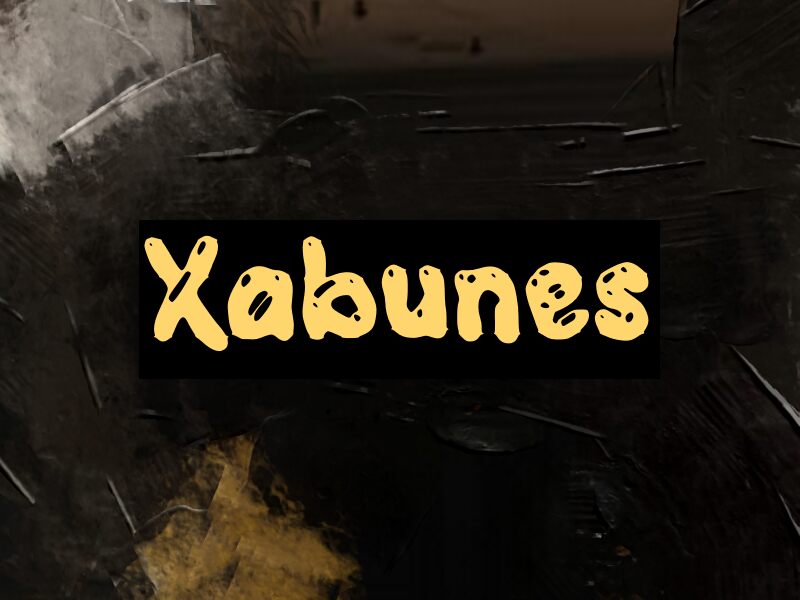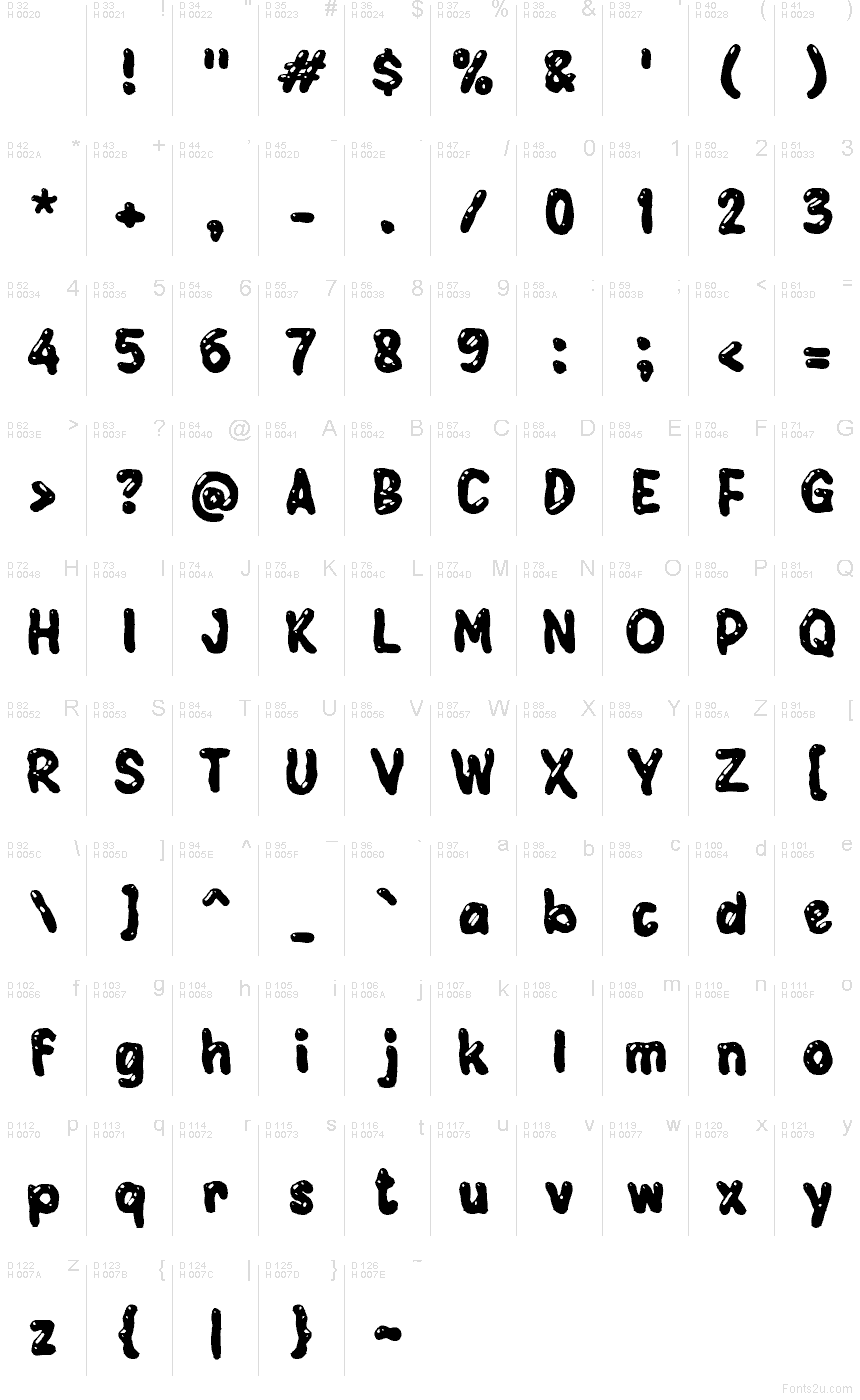
Xabunes
Xabunes de Wep es una tipografía display gratuita de estilo cartoon que parece hecha de letras negras hinchadas, con cortes blancos brillantes y bordes derretidos. Esta superficie lustrosa, con un acabado como de presión manual, le otorga al diseño una textura gomosa propia del cómic; las letras se sienten más como gotas de tinta o pegatinas que como caracteres tipográficos convencionales.
Este estilo encaja a la perfección en portadas de libros infantiles, envoltorios de dulces, encabezados de cómics, invitaciones a fiestas y miniaturas divertidas para YouTube. Especialmente en títulos cortos y logotipos, la redondez de sus formas y sus pequeños brillos logran convertir cualquier palabra en un elemento gráfico lleno de personalidad.